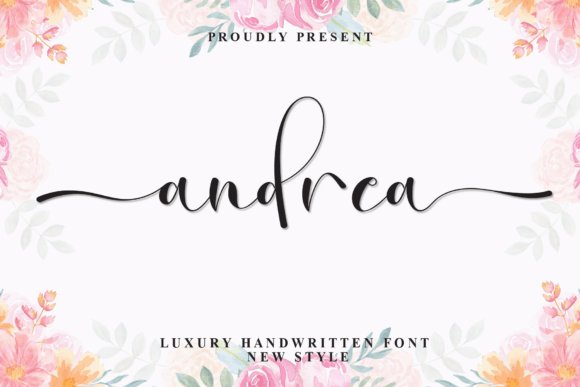
Andrea
Att hitta rätt designelement kan vara utmanande, men Andrea erbjuder en exceptionell samling som omedelbart lyfter ditt arbete.
Oavsett om du skapar POD-produkter (Print on Demand), bröllopsinbjudningar eller grafik för sociala medier, är Andrea ett perfekt val.